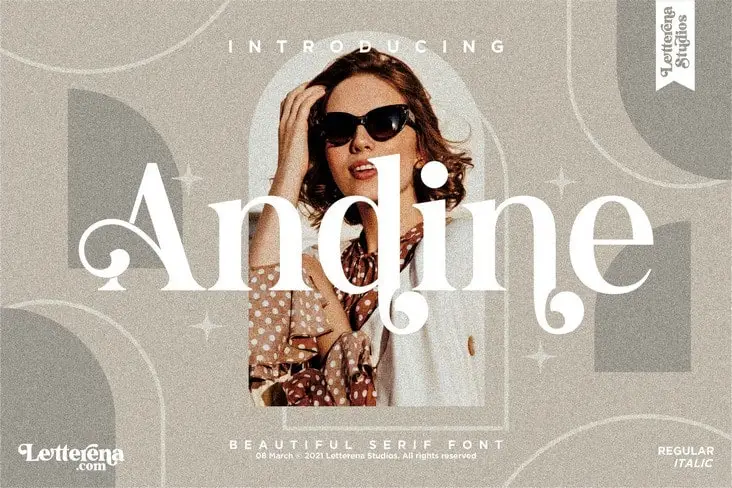
Andine Serif Font – Fonte Grátis
Andine Serif Font
Andine Serif é uma fonte serif moderna com traços florais para deixar seu projeto único e encantador. Com alternativas que a tornam perfeita para uma ampla variedade de projetos, como logomarcas, identidades corporativas, designs para móveis de casa, embalagens de produtos, tigelas, estampas em frases, cartazes, sacolas de compras, camisetas, capas de livros, selos de cartão-postais, envelopes de convite, cartões de agradecimento, etiquetas, fotografias e até mesmo eventos especiais. Sua beleza elegante é perfeita para qualquer projeto que exige um sabor de serif, seja eleluxuoso ou belo. Experimente Andine Serif e deixe seu próximo trabalho brilhar ainda mais.